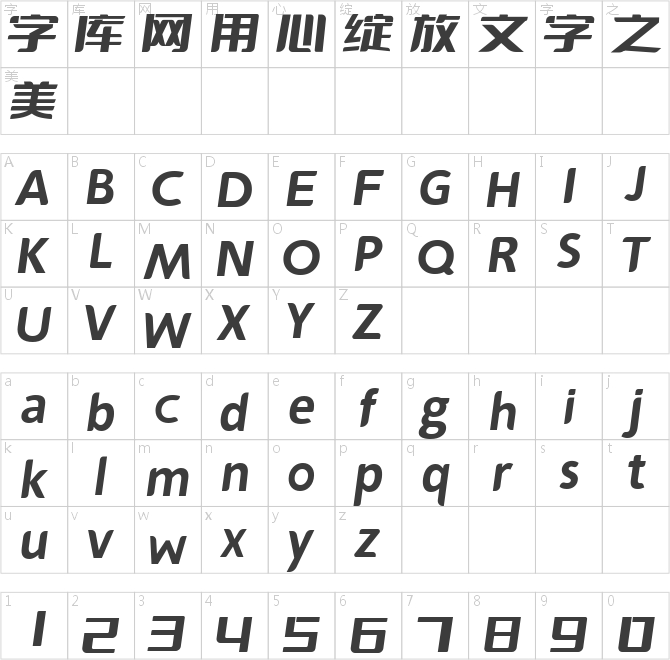
斗魚(yú)追光體字體下載douyuFont
斗魚(yú)追光體,是由斗魚(yú)武漢研發(fā)部UED提供指導(dǎo),品牌組設(shè)計(jì)成員主導(dǎo)設(shè)計(jì)的全新品牌字體。很多人會(huì)問(wèn),斗魚(yú)為什么要設(shè)計(jì)自己的字庫(kù),我們并非心血來(lái)潮,作為一個(gè)在國(guó)內(nèi)知名的直播平臺(tái)公司,我們需要統(tǒng)一的字體來(lái)發(fā)聲,來(lái)表現(xiàn)企業(yè)自身的風(fēng)格,并且向外界傳遞我們自己的品牌特質(zhì)。我們也想統(tǒng)一公司內(nèi)所有的子品牌標(biāo)志與各項(xiàng)目的宣傳形象,在視覺(jué)上用同一種聲音來(lái)凸顯斗魚(yú)。我們希望用戶想到斗魚(yú)公司時(shí),是會(huì)聯(lián)想到一個(gè)具有活力、上進(jìn),且具有娛樂(lè)性質(zhì)的科技型公司。我們?cè)O(shè)計(jì)團(tuán)隊(duì)也是秉承著這些,來(lái)設(shè)計(jì)這套字體。